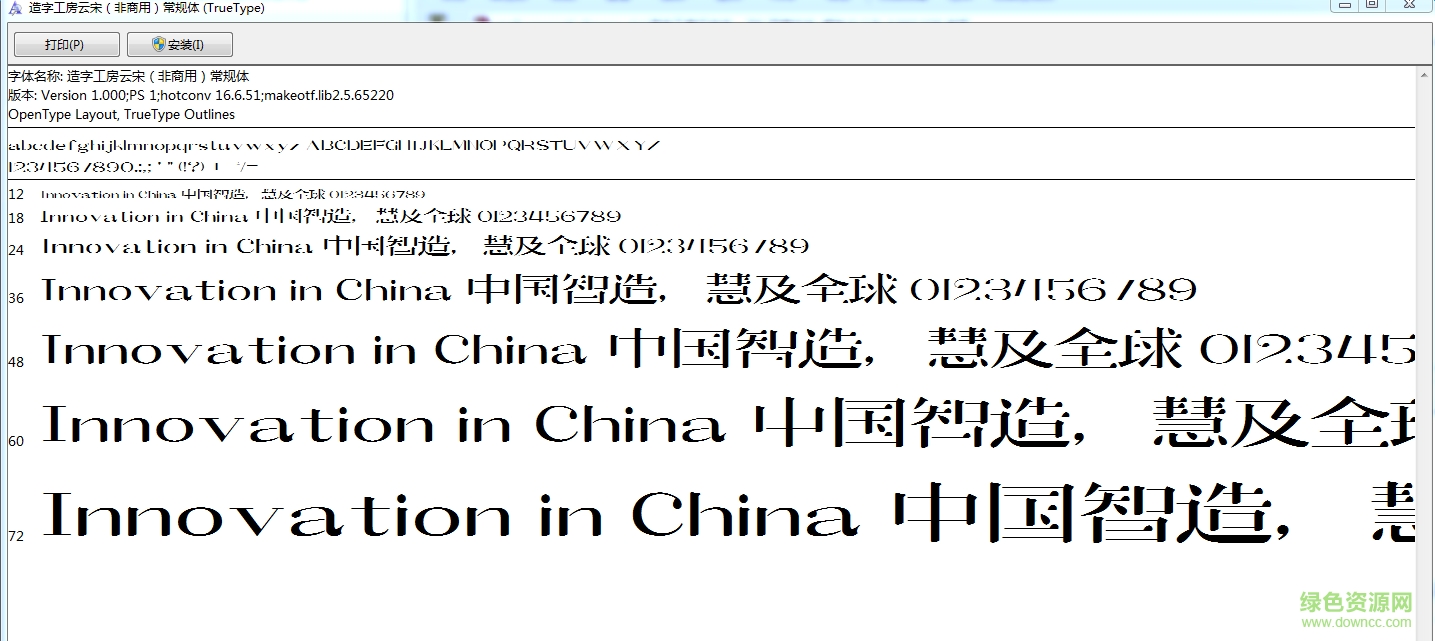
造字工房云宋體是一款造字工房類清新優(yōu)雅風(fēng)格字體軟件,云宋體整體效果相輔相成,比較有情趣,在標(biāo)題內(nèi)容設(shè)計(jì)方面有著不錯(cuò)的應(yīng)用,同時(shí)也深受廣大書(shū)法家的喜愛(ài),還有更多好看字體盡情期待,歡迎到綠色資源網(wǎng)下載體驗(yàn)!
造字工房云宋體橫細(xì)豎粗,筆畫(huà)新穎獨(dú)特,恰如待放荷苞的點(diǎn)與橫右端的“露滴”相得益彰,互相呼應(yīng),增強(qiáng)一份意境。結(jié)構(gòu)上采用扁體,筆畫(huà)之間分離,但不影響字形的識(shí)別性。整套字體清新雅淡,情趣盎然。此款字體適用于標(biāo)題、廣告或正文用字。有著極強(qiáng)的應(yīng)用空間。